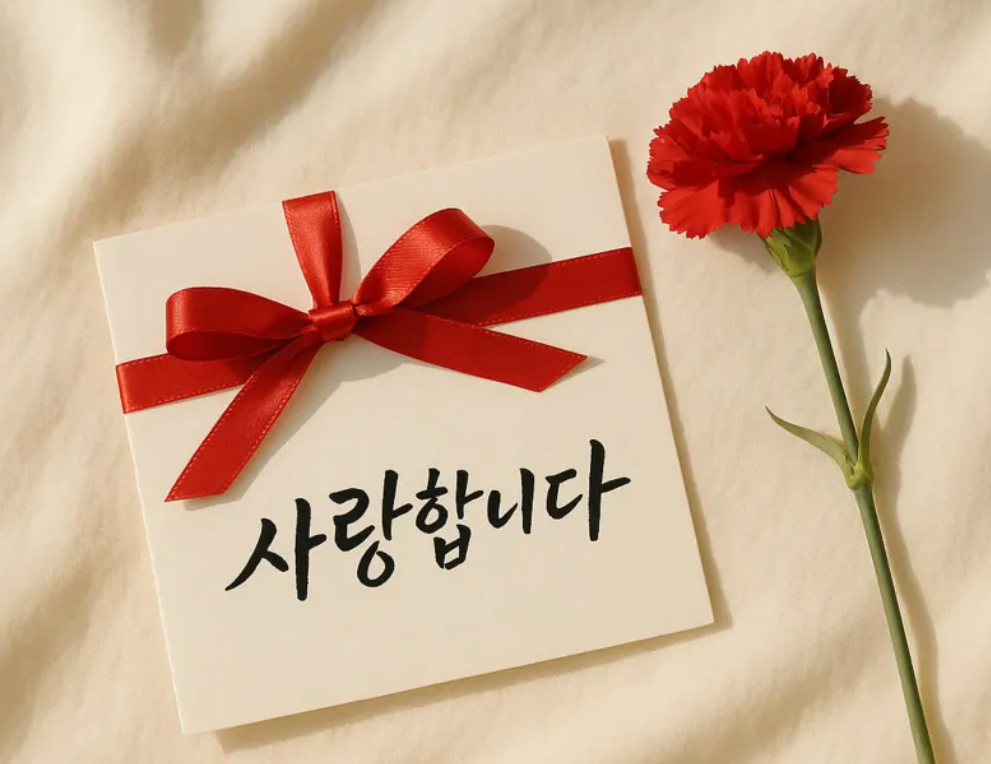
바른 글씨체를 만들기 위한 필수 연습법 예쁜 글씨를 만들기 위해서는 단순히 따라 쓰는 것만으로는 부족해요. 바른 글씨체를 갖추려면 손의 힘 조절, 균형 감각, 필기 속도 등을 모두 고려해야 해요. ✍
오늘은 바른 글씨체를 만들기 위해 꼭 실천해야 하는 핵심 연습법 5가지를 알려드릴게요. 이 연습을 꾸준히 하면 글씨가 한결 깔끔해질 거예요! 😊
📏 기본 선과 획 연습하기
바른 글씨체의 기본은 정확한 선과 획을 그리는 것부터 시작돼요. 글씨를 쓰는 과정은 마치 그림을 그리는 것과 비슷하기 때문에 획을 일정하게 긋는 연습을 충분히 해야 한답니다. ✍
글씨가 삐뚤빼뚤하거나 균형이 맞지 않는 경우, 대부분 선을 정확하게 긋지 못하는 경우가 많아요. 따라서 먼저 직선, 곡선, 대각선 등의 기본 선을 연습하면 획이 일정한 예쁜 글씨를 만들 수 있어요. 😊
📝 기본 선과 획 연습 방법
연습 방법 설명 효과 직선 긋기 가로선, 세로선을 일정한 간격으로 긋기 글씨의 안정감 향상 곡선 연습 부드러운 곡선을 반복해서 그리기 획이 자연스럽고 유연해짐 대각선 연습 균일한 기울기로 대각선 긋기 글씨의 균형감 향상 원 반복 연습 동그라미를 균일하게 반복해서 그리기 부드러운 필기감 형성 이러한 연습을 꾸준히 하면 글씨를 쓸 때 획이 일정하고 균형 잡힌 형태를 유지할 수 있어요. 😊 그렇다면 다음으로 글씨 크기와 간격을 맞추는 방법을 알아볼까요? 🎯
📐 글씨 크기와 간격 조절하기
바른 글씨체를 가지려면 글씨 크기와 간격을 일정하게 유지하는 것이 중요해요. 글씨 크기가 들쑥날쑥하거나, 글자 간격이 너무 좁거나 넓으면 전체적인 가독성이 떨어지고, 보기에도 깔끔하지 않아요. ✍
많은 사람들이 글씨를 연습할 때 크기와 간격을 맞추지 않고 무작정 따라 쓰는 경우가 많아요. 하지만 일정한 크기와 간격을 유지하는 연습을 하면 훨씬 더 정돈된 글씨체를 만들 수 있어요! 😊
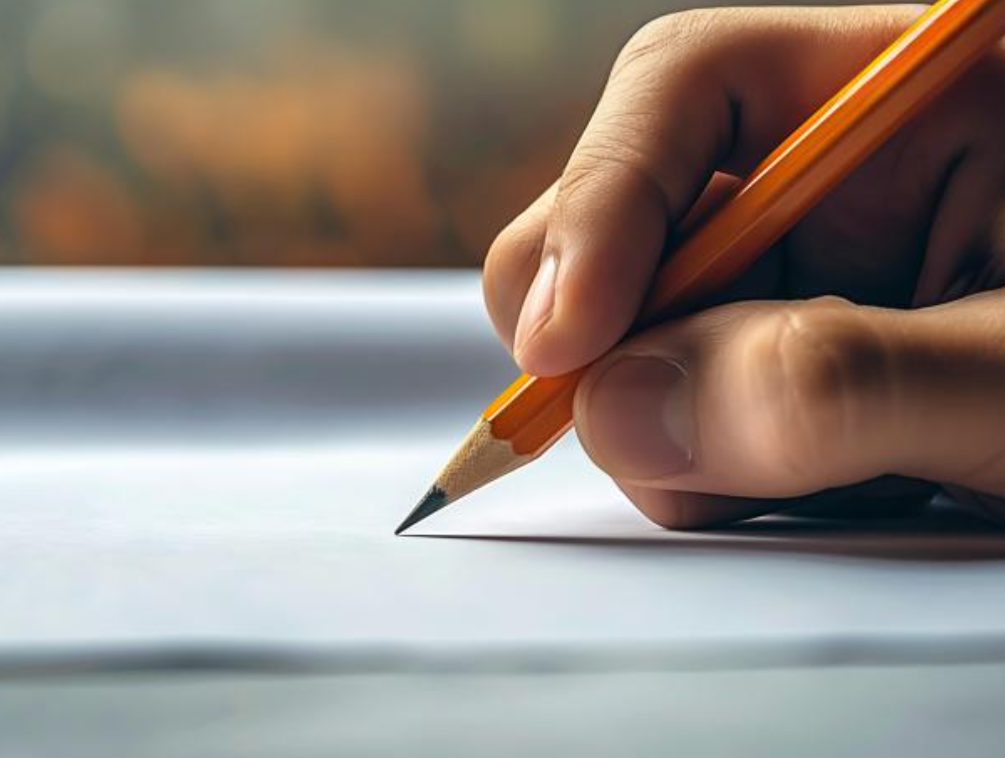
글씨 크기와 간격 조절하기 📏 글씨 크기와 간격 조절 연습법
연습 방법 설명 효과 모눈 종이에 쓰기 모눈 칸을 활용하여 일정한 크기로 글자 쓰기 글자 크기 균형 유지 줄 간격 맞춰 쓰기 가이드라인을 사용해 일정한 줄 간격 유지 가독성 높은 글씨체 형성 글자 사이 일정하게 쓰기 각 글자 사이에 균일한 간격 유지 글씨가 정돈되어 보임 큰 글씨 → 작은 글씨 연습 처음에는 크게 쓰고 점차 줄여가며 쓰기 손 근육 조절 능력 향상 이 연습을 꾸준히 하면 글씨 크기가 일정해지고, 가독성이 뛰어난 깔끔한 글씨체를 완성할 수 있어요. 😊 그럼 이제 글씨를 쓸 때 가장 중요한 ‘손의 힘 조절과 필기 속도 맞추기’ 연습을 알아볼까요? 🚀
✋ 손의 힘 조절과 필기 속도 맞추기
바른 글씨체를 만들려면 손에 적절한 힘을 주고, 필기 속도를 조절하는 것이 중요해요. 너무 힘을 주면 손이 쉽게 피로해지고, 너무 빨리 쓰면 글씨가 흐트러질 수 있어요. ✍
적절한 힘 조절과 필기 속도를 유지하면 획이 부드럽고 일정한 글씨체를 만들 수 있어요. 따라서 손가락과 손목의 힘을 균형 있게 분배하는 연습이 필요하답니다. 😊
🎯 손의 힘 조절 & 필기 속도 연습법
연습 방법 설명 효과 손 힘 빼고 쓰기 연필을 가볍게 쥐고 글씨를 써보기 손목 피로 감소 & 부드러운 필기체 형성 천천히 쓰기 속도를 줄이고 정확하게 글씨 써보기 획이 선명하고 안정적인 글씨체 완성 박자 맞춰 쓰기 글씨를 일정한 속도로 꾸준히 써보기 일관된 글씨체 유지 손목 스트레칭 글씨 연습 전후에 손가락과 손목 풀어주기 필기 피로 예방 & 손 근육 강화 이 연습을 꾸준히 하면 글씨가 부드러워지고, 더 오래 필기해도 손이 덜 피곤해질 거예요. 😊 그럼 이제 일정한 글씨체를 유지하는 연습법을 알아볼까요? ✍
📝 일정한 글씨체 유지하는 연습
예쁜 글씨는 일정한 크기와 모양을 유지해야 완성도가 높아 보여요. 하지만 글씨를 쓰다 보면 크기가 달라지거나 모양이 변하는 경우가 많아요. 이를 해결하려면 일정한 패턴으로 글씨를 쓰는 연습이 필요해요! ✍
특히 한 줄을 쓸 때 글자가 위아래로 흔들리거나, 글씨가 점점 작아지거나 커지는 경우가 있어요. 이런 문제를 해결하기 위해 모눈 종이나 가이드 라인을 활용하면 좋아요! 😊
📏 일정한 글씨체 유지하는 연습법
연습 방법 설명 효과 모눈 종이에 쓰기 모눈 칸 안에서 글자를 균형 있게 배치 글씨 크기와 간격 조절 능력 향상 수평선 맞춰 쓰기 가이드 라인을 따라 글씨 쓰기 글씨가 일정한 높이로 정렬됨 속도 일정하게 쓰기 너무 빠르거나 느리지 않게 균형 유지 획의 균형과 일관성 증가 동일한 단어 반복 쓰기 한 단어를 같은 크기와 형태로 여러 번 쓰기 글씨체의 일관성 유지 이 연습을 꾸준히 하면 한 페이지를 써도 글씨 크기와 간격이 일정하게 유지될 수 있어요! 😊 그럼 이제 필사 연습을 활용해 자연스럽고 부드러운 글씨체를 만드는 방법을 알아볼까요? ✍
📖 필사 연습으로 자연스러운 필기체 만들기
필사는 글씨 교정에 가장 효과적인 방법 중 하나예요. 좋은 글씨체를 따라 쓰면서 자연스럽게 손의 감각을 익힐 수 있기 때문이죠! ✍
특히 바른 글씨체를 만들고 싶다면 자신이 원하는 스타일의 글씨를 선택해 따라 써보는 것이 좋아요. 처음에는 천천히 쓰면서 획의 방향과 흐름을 익히고, 점점 속도를 올리며 자연스러운 필체를 만들면 돼요! 😊
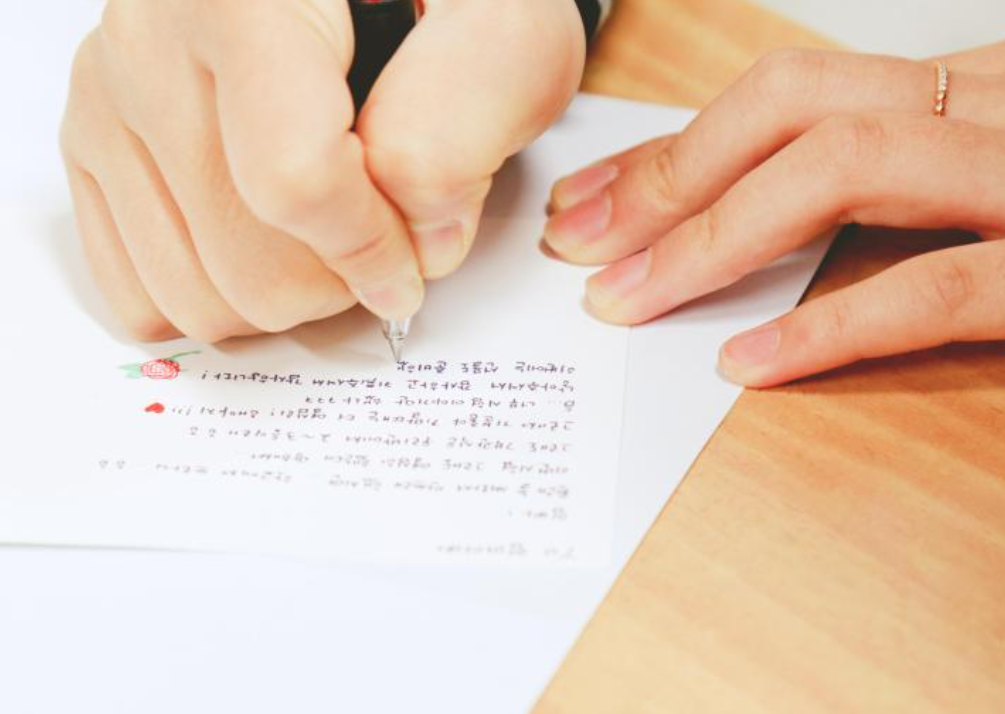
필사 연습으로 자연스러운 필기체 만들기 🖋 필사 연습법
연습 방법 설명 효과 좋아하는 문장 필사 책, 명언, 시 등 마음에 드는 문장을 선택해 따라 쓰기 자연스러운 필기체 형성 한 글자씩 천천히 따라 쓰기 획의 방향과 흐름을 정확하게 익히며 연습 획의 균형과 모양 교정 속도를 점점 올리며 쓰기 처음에는 천천히, 이후에는 자연스럽게 빠르게 쓰기 흐름 있는 필체 완성 다양한 필기구로 연습 연필, 볼펜, 만년필 등 다양한 도구 사용 필기 감각 향상 필사 연습을 하면 손이 자연스럽게 글씨체를 기억하고, 더 부드럽고 유연한 필기체를 만들 수 있어요. 😊 그럼 이제 글씨 교정을 할 때 주의해야 할 점들을 알아볼까요? ⚠
⚠ 글씨 교정 시 주의해야 할 점
글씨 교정을 할 때는 단순히 많이 쓰는 것보다 올바른 방법으로 꾸준히 연습하는 것이 더 중요해요. 잘못된 습관이 굳어지면 오히려 교정이 어려워질 수 있기 때문이에요! ✍
특히 손에 힘을 과도하게 주거나, 너무 빠르게 따라 쓰는 등의 실수는 글씨체를 망칠 수 있으므로 주의해야 해요. 아래에서 대표적인 실수와 해결 방법을 살펴볼게요! 😊
🧐 글씨 교정 시 주의해야 할 점
실수 설명 해결 방법 손에 힘을 너무 많이 줌 손이 쉽게 피로해지고 획이 부자연스러워짐 가볍게 연필을 잡고 손목을 부드럽게 움직이기 너무 빠르게 따라 쓰기 획이 흐트러지고 일정한 글씨체가 나오지 않음 처음에는 천천히 쓰면서 균형 맞추기 줄 맞추기 신경 쓰지 않음 글씨 크기와 간격이 들쑥날쑥해짐 모눈 종이 또는 가이드라인 사용 자주 필기구를 바꿈 글씨체가 일정하지 않고 필기감이 달라짐 손에 맞는 필기구를 선택하고 꾸준히 사용 위의 실수들을 피하고 바른 방법으로 연습하면 더 빠르게 예쁜 글씨체를 만들 수 있어요. 😊 그럼 이제 글씨 교정과 관련된 자주 묻는 질문을 FAQ에서 확인해볼까요? 🤔
Q1. 글씨 교정은 얼마나 하면 효과를 볼 수 있나요?
A1. 보통 하루 15~30분씩 꾸준히 연습하면 2~3주 후부터 눈에 띄는 변화를 느낄 수 있어요. 하지만 완전히 습관을 들이려면 최소 1~2개월 정도 꾸준히 연습하는 것이 좋아요! ✍
Q2. 글씨를 잘 쓰려면 어떤 필기구를 사용하는 게 좋나요?
A2. 초보자는 2B 연필이나 유성 볼펜이 좋아요. 만년필도 필압 조절에 도움이 되지만, 처음에는 너무 미끄러운 펜보다는 적당한 마찰이 있는 필기구를 선택하는 것이 좋아요. ✏🖊
Q3. 글씨 크기가 자꾸 달라지는 경우 어떻게 해야 하나요?
A3. 모눈 종이 또는 가이드라인이 있는 공책을 사용해보세요! 글자 크기를 맞추는 연습을 반복하면 점점 일정한 크기의 글씨를 쓸 수 있어요. 📏
Q4. 글씨 속도를 너무 늦추면 필기할 때 불편하지 않나요?
A4. 처음에는 천천히 연습하는 것이 중요해요. 정확한 획과 글씨 균형을 익힌 후, 점점 속도를 올리면서 연습하면 빠르게 써도 일정한 글씨체를 유지할 수 있어요. 🐢➡🏃♂
Q5. 악필을 완전히 교정할 수 있을까요?
A5. 네, 가능합니다! 💪 악필도 꾸준한 연습과 올바른 필기 습관을 들이면 충분히 개선할 수 있어요. 특히 ‘기본 선 연습 + 필사 연습’을 병행하면 빠르게 교정할 수 있어요.
Q6. 손에 힘을 너무 빼면 글씨가 흔들리는데 어떻게 해야 하나요?
A6. 손을 너무 힘없이 쓰면 글씨가 불안정해질 수 있어요. 연필을 적당히 잡고, 손목을 부드럽게 움직이며 쓰는 연습을 해보세요! ✋😊
Q7. 글씨체를 예쁘게 만들기 위해 필사할 좋은 문구가 있을까요?
A7. 짧고 간결한 문장이 좋아요! 예를 들어, “천 리 길도 한 걸음부터.”, “노력은 배신하지 않는다.” 같은 명언을 따라 쓰면 글씨 연습도 되고, 긍정적인 마인드도 기를 수 있어요. 📝✨
Q8. 글씨 교정을 도와주는 어플이나 도구가 있나요?
A8. 네! ‘모눈 노트 앱’, ‘디지털 필기 연습 앱’ 등을 활용하면 좋아요. 또한, 글씨 교정 워크북이나 필기용 가이드 종이를 활용하면 더욱 효과적으로 연습할 수 있어요. 📱📖
바른 글씨체를 만들기 위한 필수 연습법을 모두 알아봤어요! 이제 꾸준히 연습하면서 나만의 예쁜 글씨체를 완성해보세요! ✨